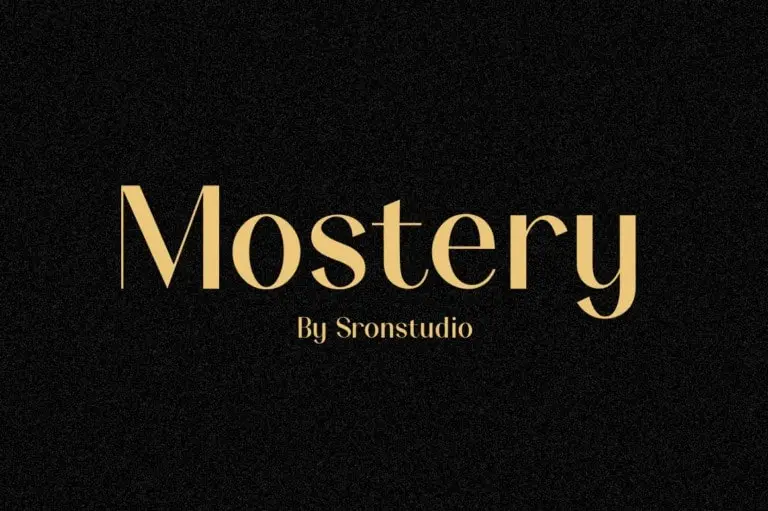
Mostery Sans Serif Font – Download Grátis
A fonte ‘Mostery Sans Serif’ é uma criação moderna e clássica do designer Sronstudio, disponível neste pacote você terá várias fontes para criar conteúdo mais atraente e inspirador para seus seguidores e clientes. Especificamente projetada para branding, convites, papéis de parede, designs de casamento, postagens na mídia social, anúncios, embalagem de produtos, design de produtos, rótulos, fotografia, marca d’água, eventos especiais e muito mais. Com a ‘Mostery Sans Serif’, suas criações ganharão um toque singular de originalidade e modernidade, tornando-a uma opção ideal para qualquer tipo de projeto gráfico onde haja necessidade de fontes sem serif.